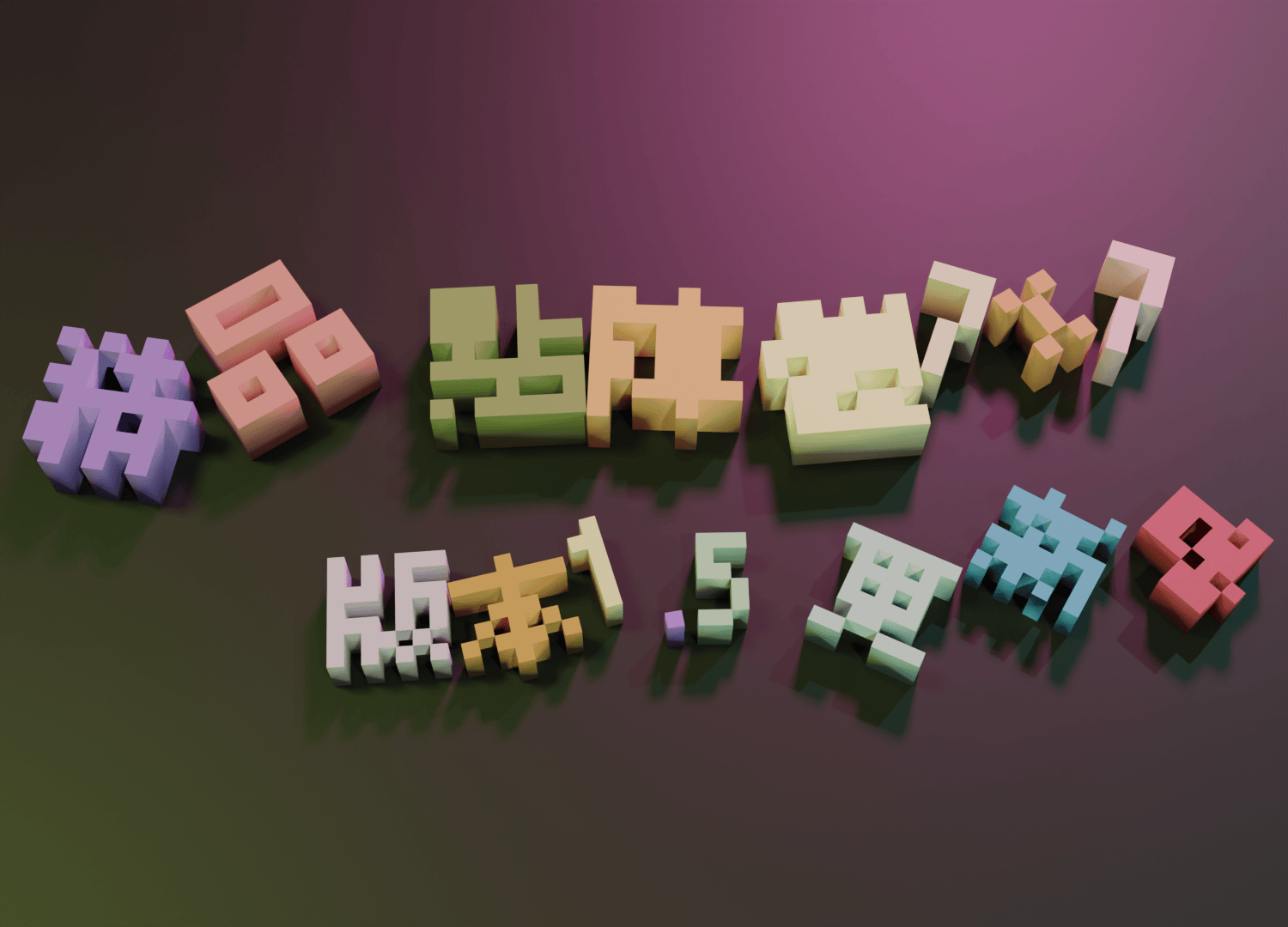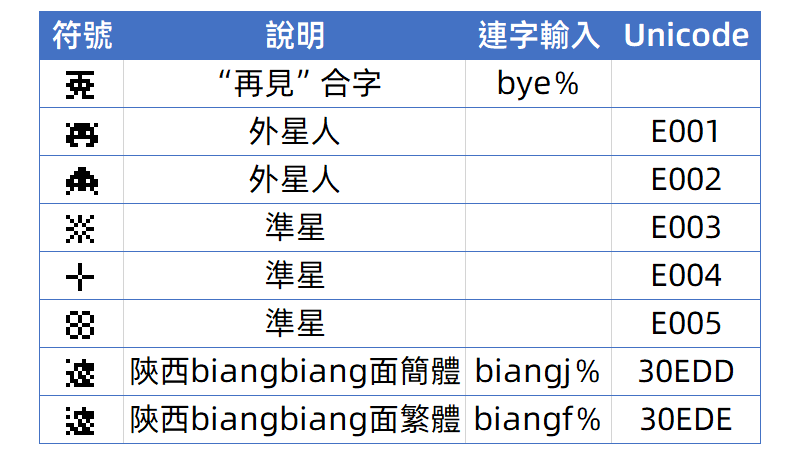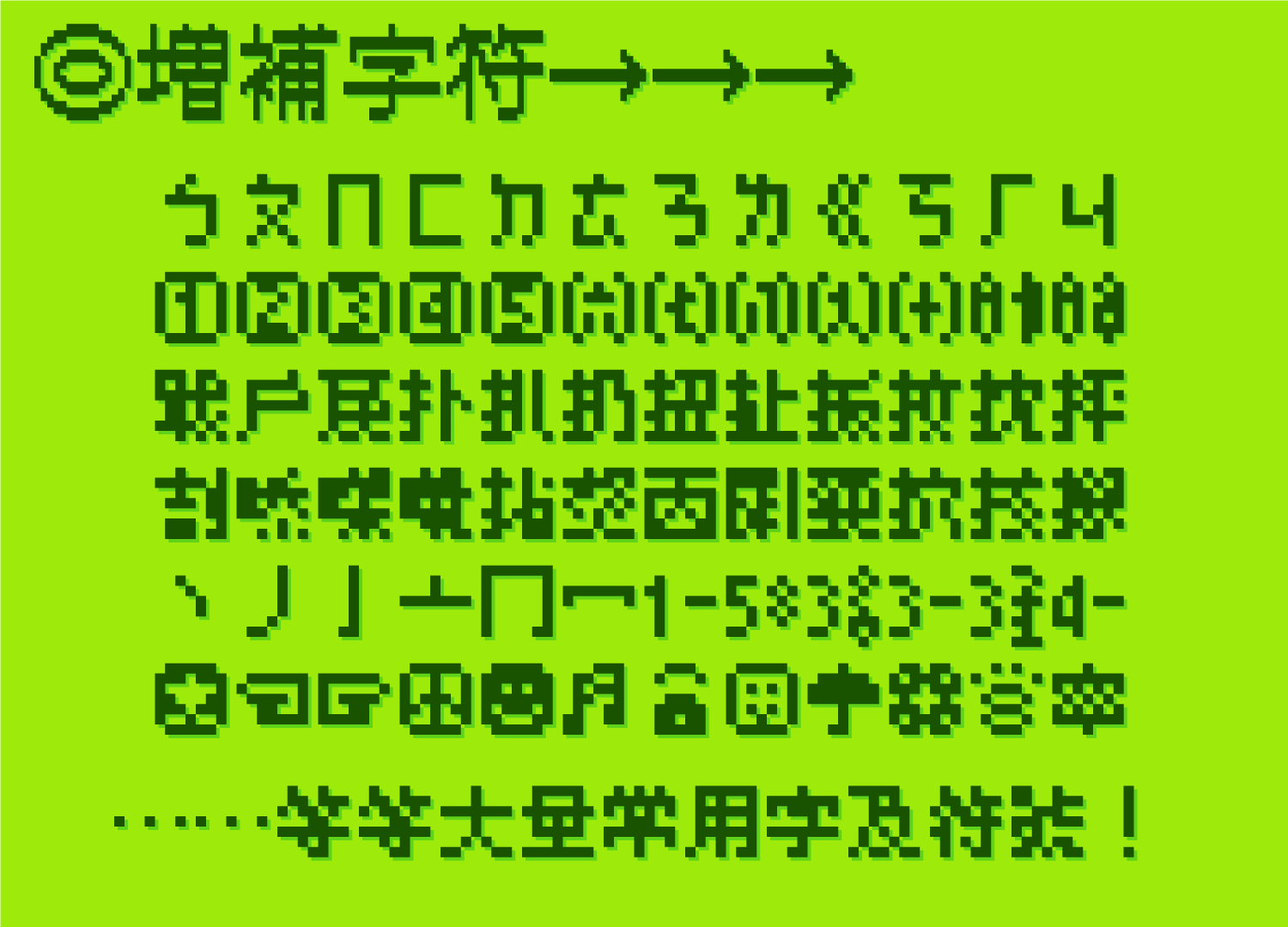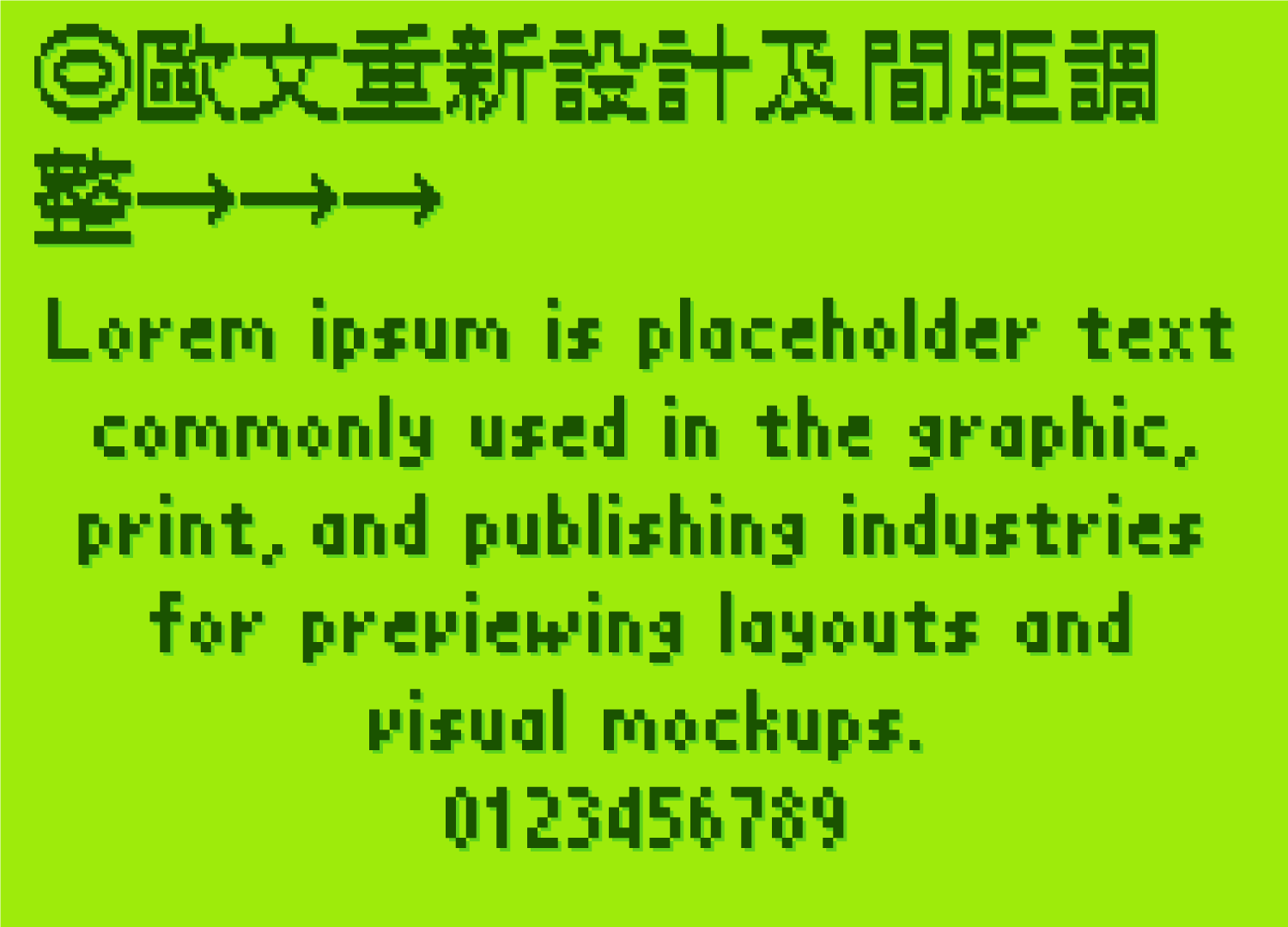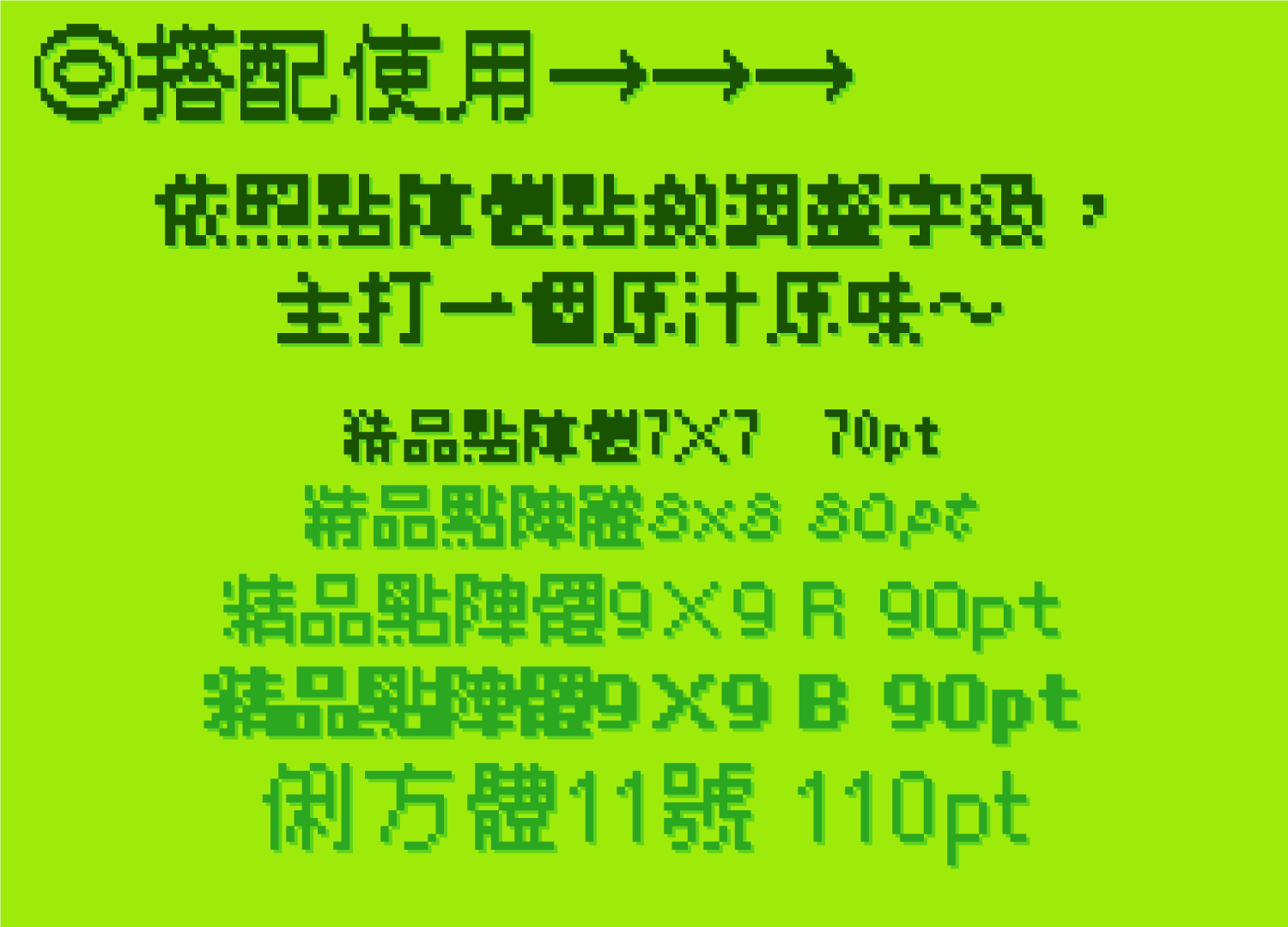
《精品点阵体 7×7 (BoutiqueBitmap7x7)》是一款基于美咲字体重新设计的字型,旨在适用于繁体中文环境的使用。我们修复了一些标点符号的写法,调整了一些日本的书写习惯,并增加了大量字符,使得这种字型更加实用!
这是一种具有非常強烈点阵风格的字体,非常适合用于像素画、游戏相关主题等领域。
所有使用的香港字符字体都支持新旧版本的香港增补字符集(GCCS+HKSCS+ISO 10646)编码。
特殊图案
该字体目前包含以下特殊字符。关于连字及 Unicode 编码的输入方式,请参阅《字言星雨体替换字使用说明》。
※请注意,汉字输入时必须按照表格中的提示进行。所有的字符都应该是半角字符,并且要注意大小写差异。如果无法输入“biang”这个字符,可以复制该字符然后粘贴进去。简体输入为:𰻝,繁体输入为:𰻞。